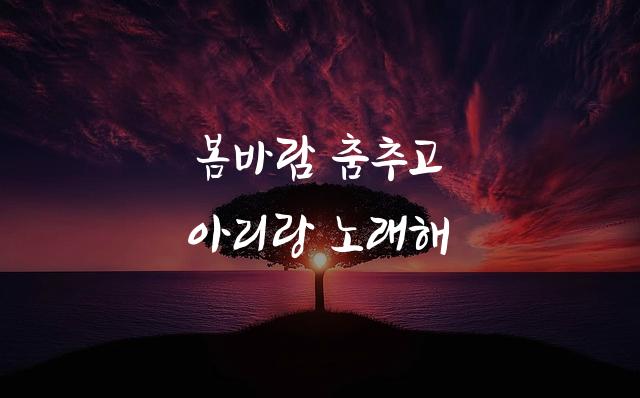
정선아리랑체는 붓글씨와 캘리그라피의 감성이 결합된 고전적인 한국어 폰트입니다. 정선군에서 제작하여 따뜻하고 정감 있는 글씨체로, 전통적인 아름다움을 현대적인 감성으로 재해석했습니다.
정선아리랑체은(는)
손글씨, 명조/전통, 펜/붓터치, 감성적인, 복고풍 계열의 생김새를 가지고 있으며
출판 디자인, 초대장, 출판물 제목 등에서 자주 활용되며, 효과적인 메시지 전달에 적합합니다.
이 폰트는 출판/미디어, 문화/예술, 이벤트/웨딩 분야에 잘 어울리며,
전통적, 세련된, 클래식한 느낌을 담고 있는 것이 특징입니다.